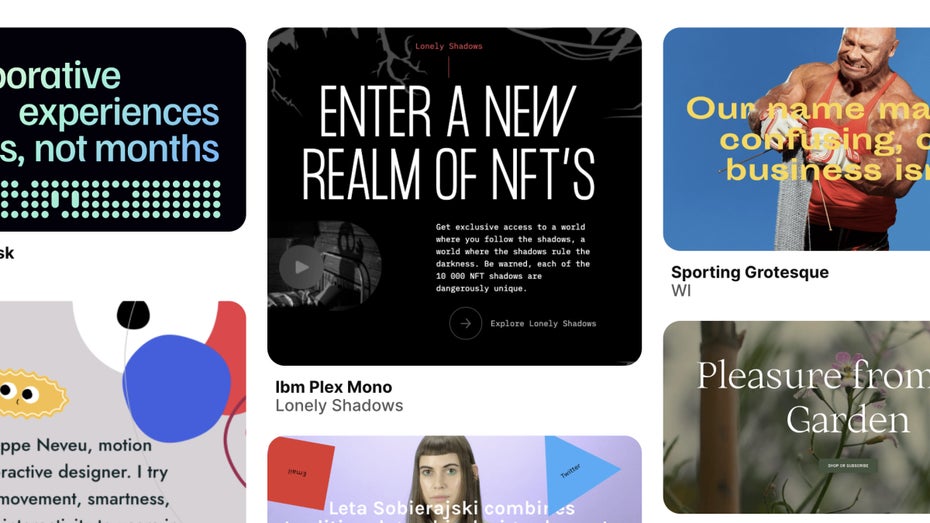
Hier findest du die besten Fonts für deine Designs
Fonts sind für Designer ein super wichtiger Baustein. Ohne sie könnten Produkte oft nicht das ausdrücken, was sie sollen. Der passende Font für die richtige Botschaft ist von großer Bedeutung.
Fonts in the Wild bietet eine bunte Auswahl an Schriftarten. (Screenshot: Fonts in the Wild)
Seit mehr als 5.000 Jahren setzt sich der Mensch mit Schriften auseinander. Vom Ritzen und Malen auf Stein bis hin zu aufwendigen Gravuren, Stempeln und Schreibwerken in der Moderne – schon immer spielte Schrift eine große Rolle in der Menschheit. Genauso wichtig ist ihre Darstellung. Allein Google Fonts führt 1.000 Schriftarten. Insgesamt gibt es weitaus mehr. Sie alle zu zählen, ist wohl ein Ding der Unmöglichkeit.
Die Seite Fonts in the Wild versucht, all diese Schriftarten aufzulisten. Die Website bietet eine breite Auswahl an Schriftarten in den Kategorien Free, Google und Adobe. Designer können hier durch eine Vielzahl an Fonts stöbern und die auswählen, die am besten zu ihrem Projekt passen. Egal, ob eine kostenlose Schriftart für ein persönliches Projekt gesucht wird oder hochwertige kommerzielle Fonts für eine professionelle Anwendung benötigt werden. Bei Fonts in the Wild kann jeder fündig werden.
Die Website ermöglicht es Nutzern, die Schriftarten einfach und effizient zu durchsuchen. Wenn sie gerne kostenlose Fonts hätten, können sie gezielt nach dieser Kategorie filtern und eine Vielzahl von Optionen entdecken. Für diejenigen, die Schriftarten von Google oder Adobe bevorzugen, bietet die Website ebenfalls spezifische Filteroptionen. Somit können Nutzer das Suchergebnis genau auf ihre Bedürfnisse abstimmen und die perfekte Schriftart für ihr Projekt finden.
Neben der umfangreichen Auswahl an Schriftarten bietet die Website auch einen Pinterest-Feed mit täglicher Typinspiration. Hier finden Nutzer eine Vielzahl von inspirierenden Beispielen, wie die Schriftarten in unterschiedlichen Designs eingesetzt werden können. Diese Inspiration kann helfen, neue Wege zu entdecken und kreativ zu werden.